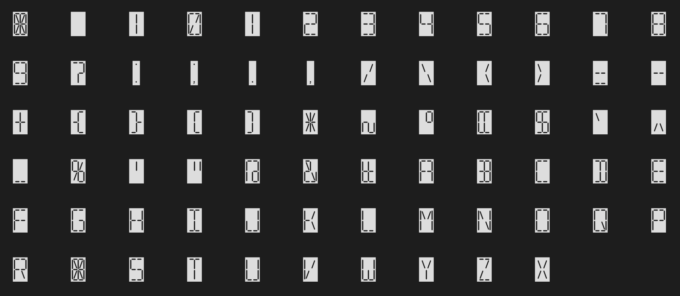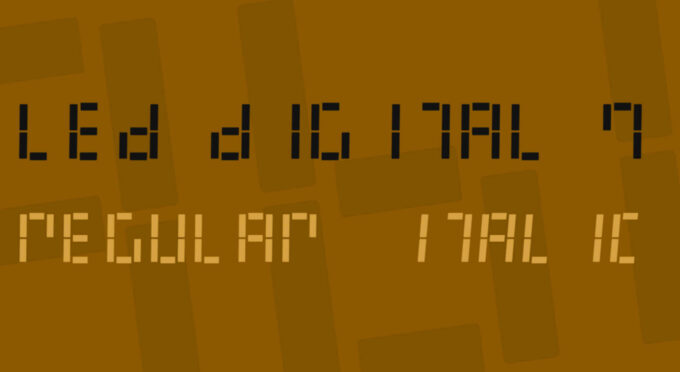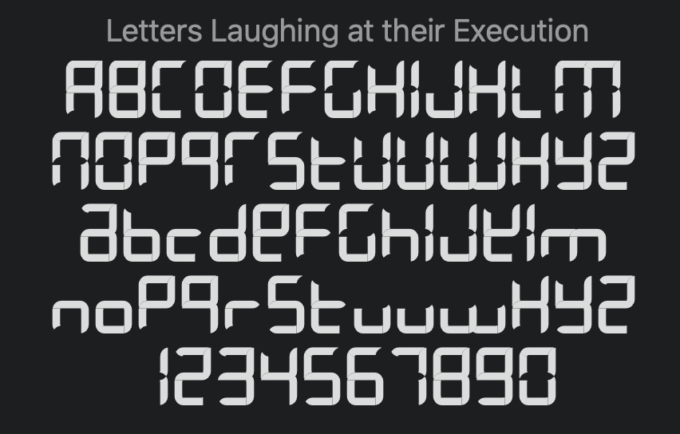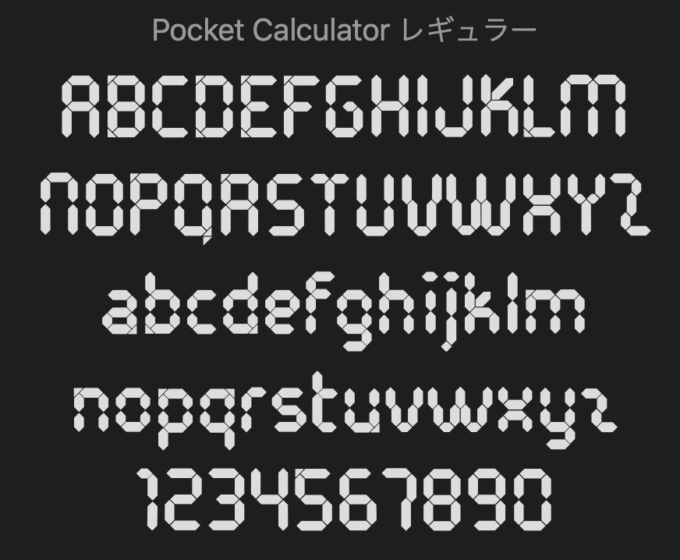
全て無料!!近未来を表現できるかっこいい『デジタルフォント素材』
今回は近未来を表現できるかっこいい『デジタルフォント素材』を紹介していきます。
Letters Laughing
19seg box
Pocket Calculator
Digital System
DJB Get Digital
LED Digital 7
Digital Dark System
Trias
Digitalism
High speed
Digital Dust
まるこいあす
7セグ・14セグフォント 「DSEG」
Dash Digital-7
7 Segmental Digital Display